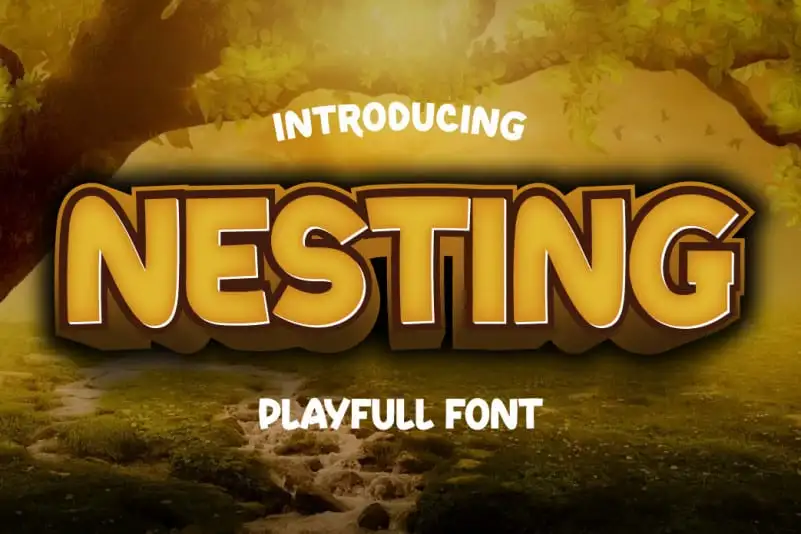
Nesting Display Font – Download Grátis
A fonte Nesting Display é perfeita para projetos que exigem uma aparência elegante e versátil. Especificamente criada pelo designer twinletter, essa fonte se destaca por sua aparência robusta e clara, com características muito definidas e poderosas. Ela não apenas adicionará um toque único a qualquer projeto visual, mas também será capaz de adaptar-se perfeitamente para diferentes contextos e estilos. A simplicidade e a clareza da Nesting Display permitem que você use a fonte em múltiplas maneiras, criando designs incríveis nos mais variados projetos de design gráfico. Seja para uma campanha publicitária inovadora ou para a criação de um logotipo impactante, essa fonte vai ajudar a garantir que seu trabalho seja sempre destaque. Experimente ela hoje e veja como essa elegância poderosa pode transformar seus projetos de design!